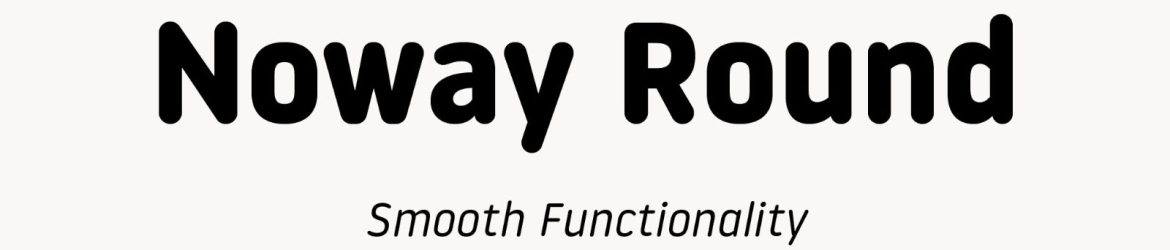
Noway Round Corporate Typeface – Download Grátis
Agora, aqui está a descrição em português para a página de download do recurso gráfico ‘Noway Round Corporate Typeface’, em dois parágrafos curtos: O Noway Round Corporate Typeface é uma nova adição à família Noway, desenvolvida inicialmente para uso corporativo e assinatura. Esta fonte oferece uma ampla gama de opções, incluindo 10 pesos diferentes, além de um pacote de 159 ícones adicionais. Ideal para branding, assinatura, embalagem, e mais, essa fonte é flexível o suficiente para atender a uma variedade de necessidades. Com múltiplas línguas incluídas e suporte para numerário e frações, a fonte atende a todas as suas necessidades de marca. Além disso, o Noway Round Corporate Typeface traz um estilo único e moderno, tornando-se uma excelente escolha para empresas que desejam uma identidade visual única e moderna.